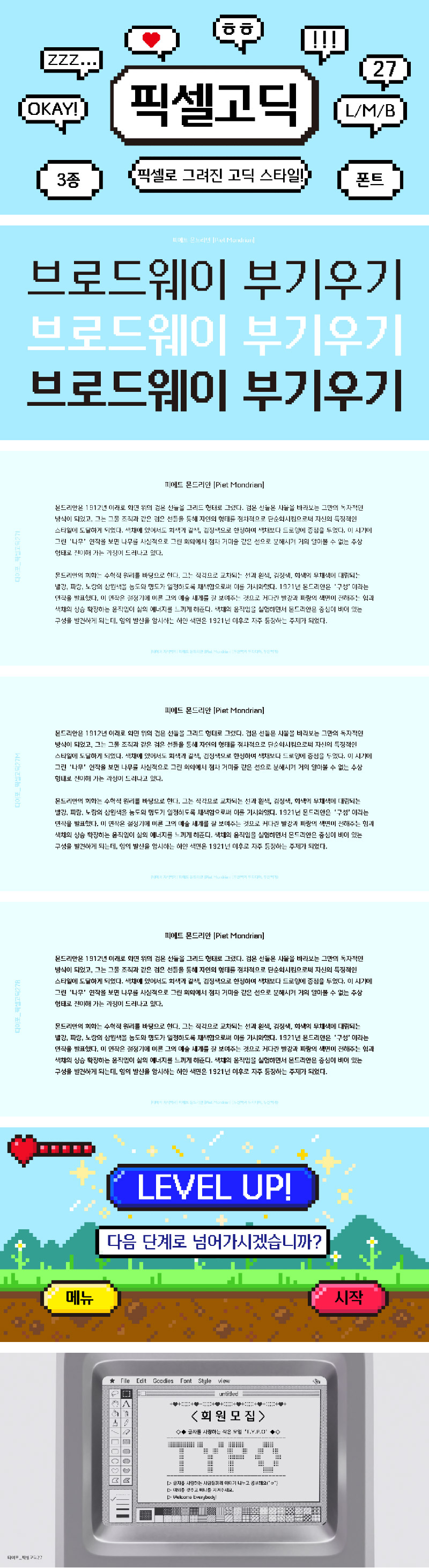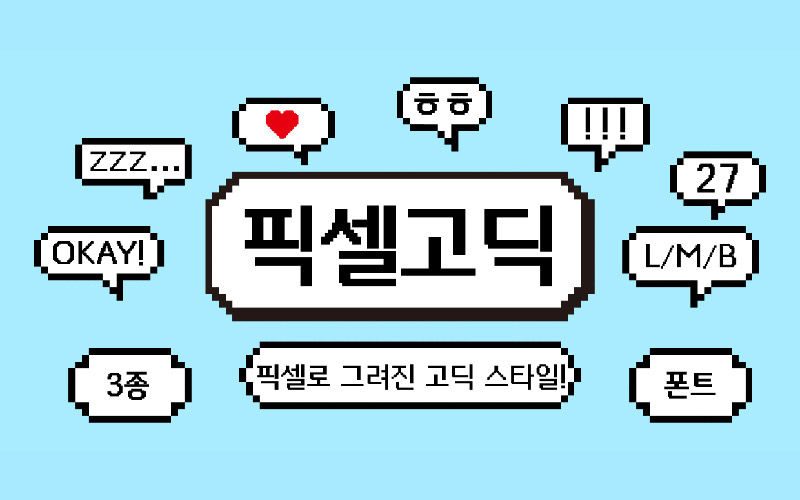
타이포_픽셀고딕27
3 종 - Bold, Medium, Light픽셀고딕27 글꼴은 고딕 기본 구조에 비트맵 스타일을 적용시켜 만든 서체입니다.
점과 점이 모여 선을 이루고, 선과 선이 모여 면을 만드니 곡선 없이 직선으로만 이루어진 서체가 만들어졌습니다.
작은 크기로 볼 땐 일반 고딕서체로 보이지만 크게 확대했을 때 드러나는 계단식 구조가 돋보인다는 점이 폰트의 매력적인 부분입니다.
| 폰트명 | 타이포_픽셀고딕27 / Typo_PixelGothic27 |
|---|---|
| 폰트디자인 | 정다은 |
| 디자인디렉팅 | 임진욱 |